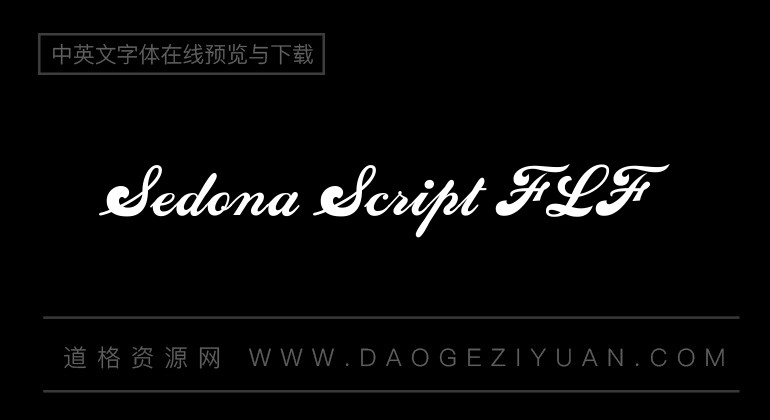
Sedona Script FLF
Sedona Script FLF是一种装饰性手写字体,由字体设计师 Casady & Greene 于1993年开发。这种字体设计灵感来自于美国亚利桑那州的一个城市 Sedona,因其美丽的自然景观和神秘的氛围而闻名。 Sedona Script FLF 字体的特点是其流畅的曲线和精美的装饰,适用于多种场合,如餐厅菜单、演出海报、手写信件等。这种字体还包括了一些特殊字符和符号,如标点符号、数字和货币符号等,使其更加实用。 Sedona Script FLF 字体通常可用于多种操作系统和应用程序中,如Microsoft Windows、Adobe Photoshop和Adobe Illustrator等。由于其美观性和多功能性,Sedona Script FLF 字体在设计师和艺术家中非常受欢迎。
Sedona Script FLF是一款非常不错的手写艺术字体,具有很好的视觉感,适合于文化类的宣传设计、商业类品牌的广告和产品包装设计以及个性化文字排版等较多场景。